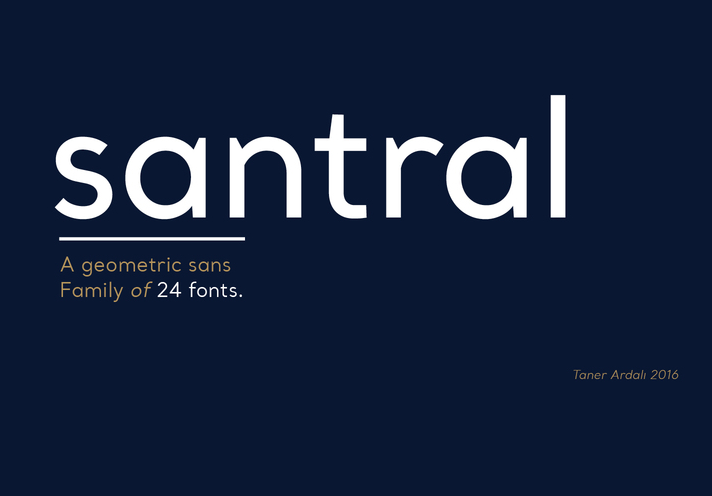
Introduzimos a nova família de fontes Santral, desenvolvida por Taner Ardali. Santral é uma tipografia projetada para alcançar um equilíbrio perfeito entre a perfeição geométrica e o impressiono ótico. A forma aguda e precisa de Santral traz resultados claros e fiáveis à comunicação com o leitor. Com 12 pesos e versões itálicas, incluindo valores de espaço inter-caracteres (kerning) e características de layout em OpenType, a Santral oferece todos os elementos typográficos necessários para alcançar o melhor resultado no design de layouts. Esta nova fonte é uma excelente opção para aqueles que buscam um equilíbrio entre simplicidade moderna e precisão.